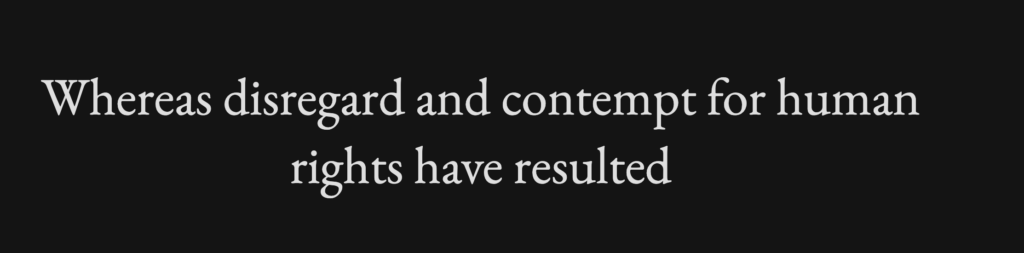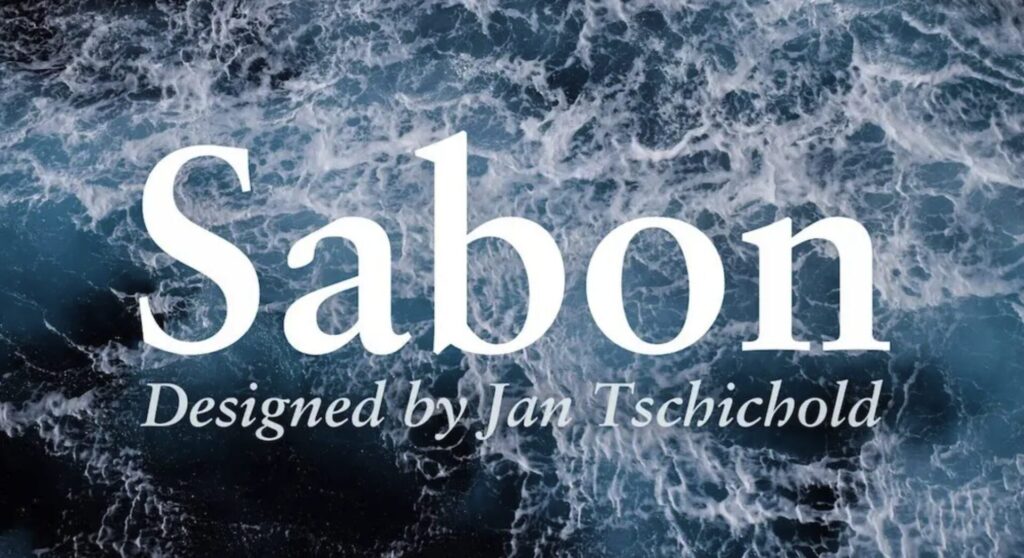
Font นี้มีของ! ใช้ทำคอนเทนต์แล้วดี มีเสน่ห์ งานปัง เงินปั๊วะ
เคยไหมที่เลือกภาพมาอย่างดี สีมาอย่างเป๊ะ คอนเทนต์ก็เขียนมาอย่างตั้งใจ แต่ทำไมยังรู้สึกขาดอะไรบางอย่างไปในงาน? ทำไมถึงยังไม่สมบูรณ์แบบและไม่ดึงดูดเท่าที่ควรเลย แต่พอลองเปลี่ยน ฟอนต์ งานกลับดูดีขึ้นทันทีแบบไม่ต้องแก้อะไรเพิ่มเลย เหมือนจิ๊กซอว์ที่หายไป แล้วพอใส่เข้าไปได้ถูกชิ้นทุกอย่างก็ลงล็อก
ครั้งนี้เราจะมาคุยเรื่องฟอนต์ที่ช่วยให้งานปัง ดึงดูด เหมาะกับสามมูเตลู ใช้แล้วงานอู้ฟู่ถูกใจชาวผู้ชอบพึ่งพาดวงชะตา
ฟอนต์คืออะไร ทำไมมันถึงมีพลังขนาดนั้น?
ฟอนต์ (Font) ไม่ใช่แค่ตัวหนังสือที่เอาไว้อ่าน แต่เป็นสิ่งที่สะท้อนบุคลิกของแบรนด์ อารมณ์ของงาน หรือแม้แต่พลังงาน ของคอนเทนต์ ถ้าเราทำโปสเตอร์งานแต่งแต่ใช้ฟอนต์แนวคอมิคเด้ง ๆ แบบการ์ตูน งานจะดูน่ารักก็จริง แต่ฟีลโรแมนติกหายหมด หรือถ้าทำคอนเทนต์สายหรู แต่ดันเลือกฟอนต์แนวสายลุยบู๊ ๆ ก็อาจพังได้โดยไม่รู้ตัว
ฟอนต์ที่ดีควรจะช่วยให้
• คอนเทนต์มีเสน่ห์มากขึ้น: ฟอนต์บางแบบให้ความรู้สึกอ่อนโยน บางแบบดูจริงจัง บางแบบมีความ playful เลือกให้ตรงกับเนื้อหาก็ช่วยส่งอารมณ์ได้ดี
• คนอ่านรู้สึกว่าเนื้อหาน่าเชื่อถือขึ้น: ฟอนต์ที่ดูอ่านง่ายและเหมาะสมทำให้คนรู้สึกว่าคุณตั้งใจ ไม่ใช่แค่ทำส่งๆ
• แบรนด์ดูมีเอกลักษณ์: ฟอนต์คือส่วนหนึ่งของภาพลักษณ์ ถ้าเลือกดี งานออกแบบจะดูเป็นมืออาชีพขึ้นทันตา
แล้วเกี่ยวอะไรกับความมู?
ถึงแม้จะเป็นอะไรที่อธิบายเหตุผลยาก แต่หลายคนก็เคยรู้สึกเหมือนกันว่าบางครั้งแค่เปลี่ยนฟอนต์ งานก็ดูเรียกลูกค้าได้แบบไม่รู้ตัว เหมือนพอเราเลือกองค์ประกอบของงานได้ลงตัว ถูกที่ ถูกจังหวะ ทุกอย่างก็เข้ามาเอง
ถ้าจะเปรียบเทียบง่าย ๆ มันก็คล้ายกับการเลือกสีเสื้อให้เหมาะกับวันเกิด หรือการวางโลโก้ให้ถูกทิศตามฮวงจุ้ย บางคนอาจจะมองเป็นเรื่องเชื่อครึ่งไม่เชื่อครึ่ง แต่ถ้าลองคิดดี ๆ มันคือการสร้างความมั่นใจจากข้างใน
พอเราใส่ใจในรายละเอียดเล็ก ๆ แบบนี้ ตั้งแต่เรื่องโทนสี ฟอนต์ ไปจนถึงการจัดวาง ทุกอย่างมันสะท้อนพลังงานที่เราส่งออกไป เวลาทำคอนเทนต์ที่เราอินกับมันจริง ๆ เราจะรู้สึกมั่นใจสุด ๆ
พูดมาถึงขนาดนี้แล้ว เราจะขอแนะนำ Font น่าใช้สำหรับสายมูให้ทุกคนได้ลองไปใช้ดูกัน
1. Garamond
ฟอนต์ระดับตำนาน คลาสสิกมาก เหมาะกับงานที่อยากให้ดูน่าเชื่อถือ ดูผู้ดี มีความรู้ลึกซึ้ง ถ้าทำคอนเทนต์แนวเล่าเรื่อง แนะนำ แบรนด์สายหรู สาย minimal ใช่เลย
2. Sabon
เป็นฟอนต์ที่มีความอ่อนโยนนิด ๆ เหมือนมีความละมุนแฝงอยู่ เหมาะกับงานที่อยากให้ดูเข้าถึงง่าย มีระดับ แต่ไม่ห่างเหิน
3. Good Vibes
ชื่อก็บอกอยู่แล้วว่าสายพลังบวก ฟอนต์ตัวนี้เหมาะกับคอนเทนต์ที่อยากให้ดูสดใส ชวนให้ยิ้ม ใช้ในพวกโพสต์สร้างแรงบันดาลใจ แคมเปญอารมณ์ดี หรือสินค้าแนว lifestyle ก็เหมาะ
การเลือกฟอนต์ที่เหมาะ ไม่ใช่แค่เรื่องความสวย แต่มันส่งต่อพลังงานบางอย่างออกไปให้คนรู้สึกได้ด้วย ฟอนต์สามารถเล่าอารมณ์ของแบรนด์ ทำให้ข้อความธรรมดาดูจริงจังขึ้น หรือในบางทีก็ช่วยให้เรื่องซีเรียสดูเข้าถึงง่ายขึ้นอย่างน่าประหลาด
ยิ่งถ้าเราเลือกฟอนต์ที่ "ใช่" สำหรับงาน มันจะรู้สึกได้เลยว่าเนื้อหาดูมีชีวิตมากขึ้น เหมือนกับเราใส่เครื่องรางดี ๆ ลงไปในคอนเทนต์ โดยที่คนอ่านอาจไม่รู้ตัวด้วยซ้ำว่าตัวอักษรตรงหน้าเขากำลังทำหน้าที่ให้คุณสนใจอ่านอย่างเงียบ ๆ อยู่เบื้องหลัง